サンキューシール クラフト紙 marianフォント
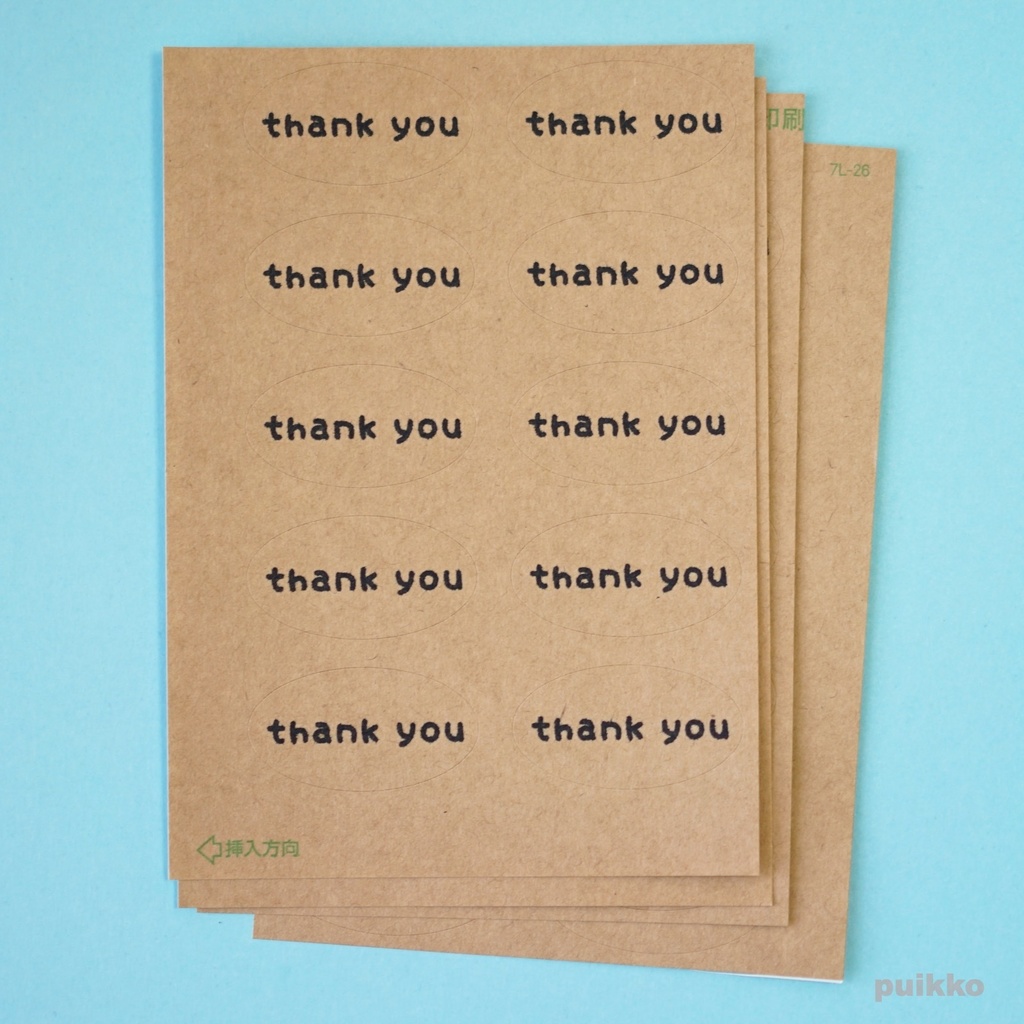
クラフト紙に印刷した楕円形のサンキューシールです。 手紙の封かん、ハンドメイド作品の梱包、ちょっとしたプレゼントのラッピングなどにお使いください。 楕円形のクラフト紙・ダークブラウンに、marianフォントというpuikkoオリジナルの丸っこいフォントで「Thank you!」の文字入り。 ・シールのサイズ 幅41×高さ22mm ・シールの片数 40片 【素材】 ラベルシール クラフト紙・ダークブラウン 【サイズ】 幅210×高さ297mm(A4判) 【購入の際の注意点】 写真と実物では多少色味が異なる場合があります。 市販のシールにインクジェットプリンタを使って印刷しているので、精密さに欠けるところがあります。あらかじめご了承ください。 A4の用紙に印刷したものを4分割して発送します。